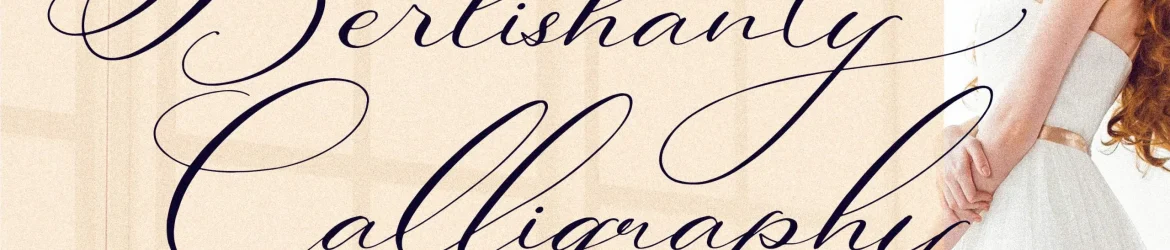
Berlishanty Calligraphy Font – Download Grátis
Esta é uma fonte de caligrafia romântica perfeita para qualquer projeto que você possa imaginar — desde logomarcas, projetos de marca até design de mobílias, embalagens de produtos e até mesmo selos. Suavizar sua identidade com esta fonte irá fazer seu trabalho soar mais amoroso e atraente. Ela se encaixa perfeitamente em designs como mugs, cartazes, sacolas de shopping, camisetas, capas de livros, cartões de nome, convites, cartão-postais, rótulos e até mesmo marcas de fotografias e marca-detragem para eventos especiais. É uma fonte que trará beleza à sua arte com um toque delicado e apropriado. Essa não é só uma fonte; ela é uma peça chave em qualquer projeto que deseja tornar especial através da caligrafia belamente elaborada.